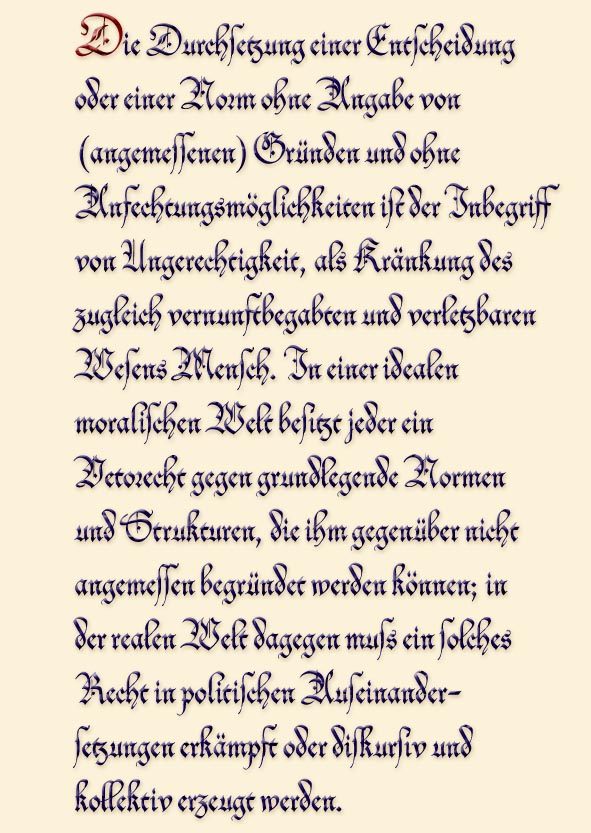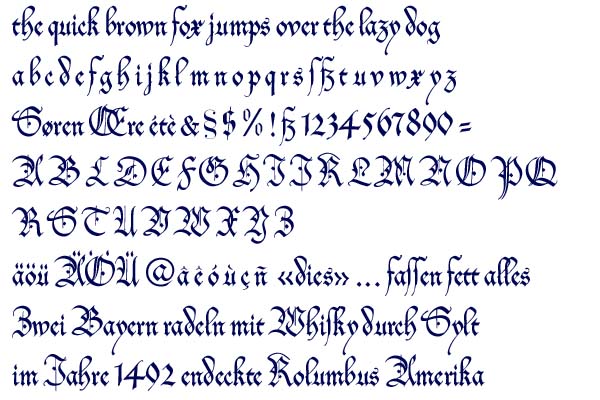
Kanzlei Script HJZ
Nach einer Zeichnung von Friedrich Heinrichsen wurde dieser Font neu digitalisiert, überarbeitet und für die Verwendung auf dem PC neu eingerichtet
Fehlende Zeichen wurden hinzugefügt und schwer lesbare durch heute gebräuchliche Zeichen ersetzt.
Um auch die nötigen Ligaturen unterzubringen, gibt es dazu noch einen 'Alternates' Font, der zudem alternative Buchstabenformen enthält.
Der Font enthält zahlreiche Kerningpaare, ist aber - wegen der komplexen Zeichen - nur bedingt bildschirmoptimiert.
This is a handwritten type blackletter, develloped and completely new designed from a handwritten sheet of Friedrich Heinrichsen. Missing letters have been added and hardly readable letters have been replaced by others. In order to add various ligatures and alternative glyphs, I developped an additional alternates font.
as being a blackletter, the font is only partly optimized for screen use
Hier ein Ausschnitt aus dem Zeichensatz. Die Schriften werden laufend verbessert, daher können einige Zeichen im Schriftsatz abweichen (z.B. K, R, ß und die Ziffern) Some of the letters in this font
Beispiel für die Anwendung des Fonts
unter Verwendung der Alternativzeichen
(Ligaturen und alternativer Zeichen)
hier: ch, li, ll, fi, r, s, si, ss, st, tzExample of Kanzlei Script using the Alternates font Set
(Ligatures und alternativer glyphs)
for: ch, li, ll, fi, r, s, si, ss, st, tz